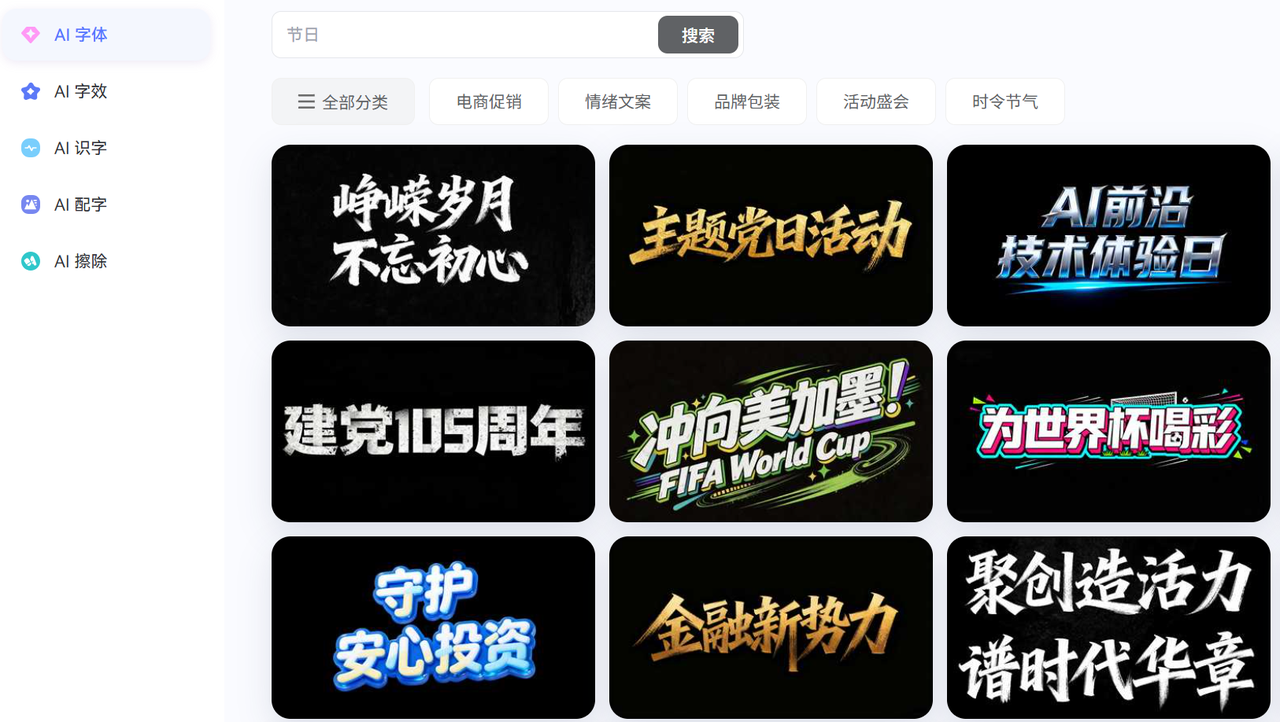
艺术字体下载合集,从基础到创意一站找齐
海报标题、品牌Logo、包装上的大字,用常规黑体宋体总显得太平淡。艺术字体自带视觉张力,一笔一画都有设计感,能让普通排版立刻变得有辨识度。但找艺术字体比找常规字体麻烦,很多平台的艺术字分类里鱼龙混杂,下载下来发现效果远不如预览图。这篇文章分享的五个渠道,从中文特效生成到海外精选库都有,帮你缩小搜索范围。
字由的分类下有不少风格强烈的字体,笔画带有装饰性细节,适合做海报主标题或者品牌标识。文艺分类则偏向优雅精致,适合做展览标题或者高端包装。这种按气质划分的方式比单纯按书体名称搜索更直觉,知道自己想要什么感觉但叫不出具体风格名时,点进对应分类浏览效率更高。
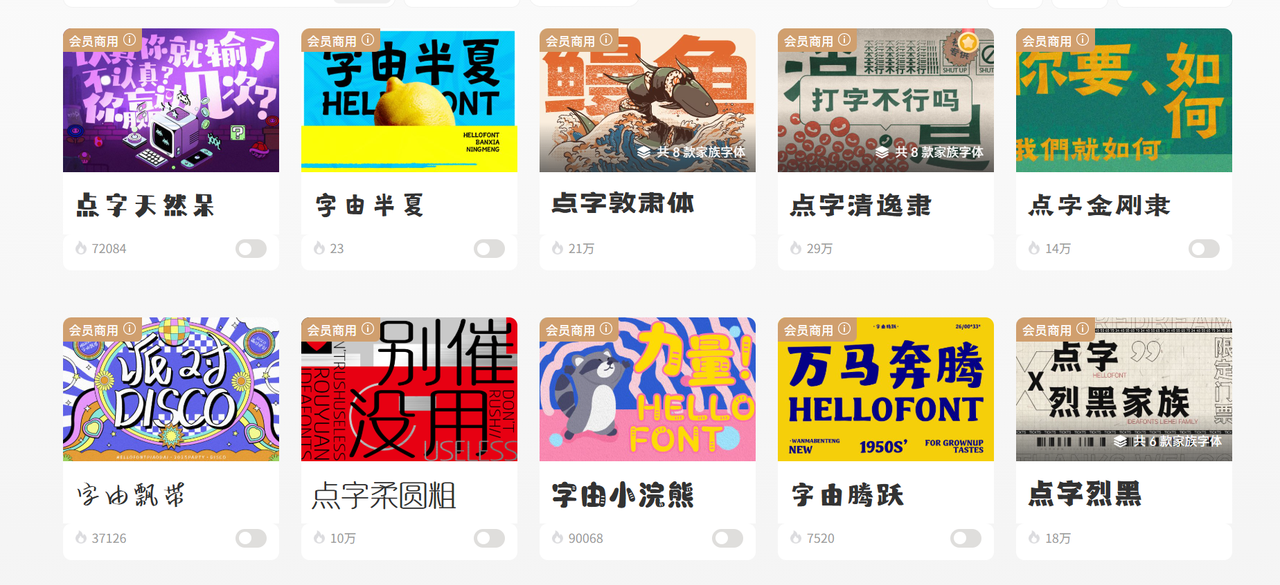
预览环节对艺术字体尤其重要。很多艺术字体在小图预览时效果不错,放大后才发现笔画细节粗糙或者字符显示不全。字由的预览框支持输入自己的文案,调整到实际使用字号后查看效果,确认清晰度再激活。激活后字体直接出现在设计软件里,不需要重启程序,试错成本很低。如果预览时发现某款艺术字体的西文部分设计得比较敷衍,和中文字形不匹配,可以立刻换另一款,避免了装完才发现不合适的尴尬。
需要把艺术字体效果再往上提一档时,字由的AI字效可以帮忙。这个工具在网页版里就能用,打开浏览器选中已激活的艺术字体,再选一个特效模板,可以给文字叠加发光、投影、渐变或者金属质感。基础面板调节字号粗细,进阶面板调整配色和效果强度,几分钟内就能拿到一张带复杂特效的PNG图片。这个功能和字体库是打通的,先在库里找到喜欢的艺术字形,再用AI字效加料,两者配合能做出常规字体文件本身实现不了的视觉效果。免费用户每日有算力额度,登录赠送的点数足够应付日常轻量使用。
2、Mockofun
Mockofun是一个在线设计工具,除了模板和图形外,也提供了字体特效生成功能。用户可以在网页里直接输入文字,选择艺术字体和特效风格,生成带设计感的标题图片。这个工具对不会用Photoshop、但又需要快速出一张带艺术字效果图片的用户比较友好。
生成的图片可以直接下载使用,也可以继续在线编辑调整。作为艺术字体下载的补充渠道,Mockofun的优势在于即开即用,不需要安装任何软件,临时在其他电脑上也能操作。对于需要快速出概念图、确认方向后再做精稿的场景,这里的生成速度比较实用。网站上还提供了不少设计模板,可以直接把生成的艺术字放进模板里出整体效果图。
3、DesignCuts
DesignCuts是一个设计资源包平台,经常推出包含多款字体的创意包。这些字体包通常围绕特定主题或者风格 curated,比如复古风格包、手写风格包、现代无衬线包等,包内的字体在视觉上比较协调,适合需要成套使用的情况。
对于需要艺术字体下载、且希望一次获取多款协调字体的用户来说,这种打包方式比逐个下载更高效。包内的字体授权信息在详情页清楚标注,大部分是允许商用的。DesignCuts还会不定期推出免费资源包,关注这些活动可以以零成本获取高品质字体包。对于做系列物料、需要保持字体风格一致性的项目来说,这里的主题包比较实用。
4、YouWorkForThem
YouWorkForThem是一个高品质设计资源站,字体板块里有不少独立设计师和字体厂牌的作品。和大型免费字体站不同,这里的选品偏向精品路线,很多字体在字形设计和完成度上比较高。艺术字体方面,平台上收录了不少Display展示字体和创意字体家族,风格从实验性到商业性都有覆盖。
每款字体都有详细的展示图,多字重家族会展示不同字重的对比效果。对于需要艺术字体下载、且对字体品质有一定要求的用户来说,这里的选品经过一定筛选,踩雷概率比较低。平台上除了字体外还有图形、模板等其他设计资源,做项目时可以在同一个平台补充素材,省去了在多个网站之间切换的麻烦。
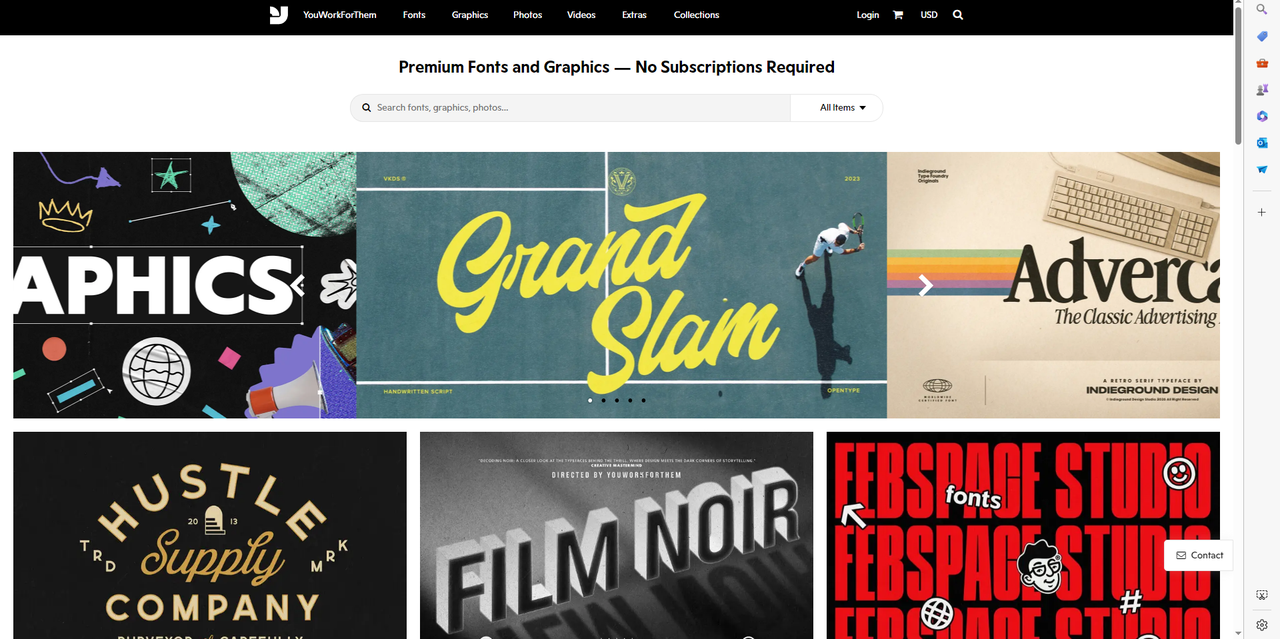
5、1001 Fonts
1001 Fonts的Artistic Fonts标签下目前收录了九百多款艺术字体,数量比较可观。顶部的标签云包括artistic、decorative、handwriting、calligraphy、modern、brand identity等关键词,点击就能快速筛选对应风格。想做复古海报就点decorative或者vintage相关标签,做现代品牌就点modern或者brand identity,找字路径比较清晰。
平台上提供Commercial free筛选按钮,勾选后只显示允许免费商用的字体,做商业项目时比较省心。每款字体都支持在线预览,输入框里填自己的文案,实时看到效果后再决定是否下载。下载按钮直接获取字体文件,安装到系统后在设计软件里就能调用。作为艺术字体下载的渠道,1001 Fonts的资源量和筛选维度都比较够用,适合批量探索不同风格的艺术字体。
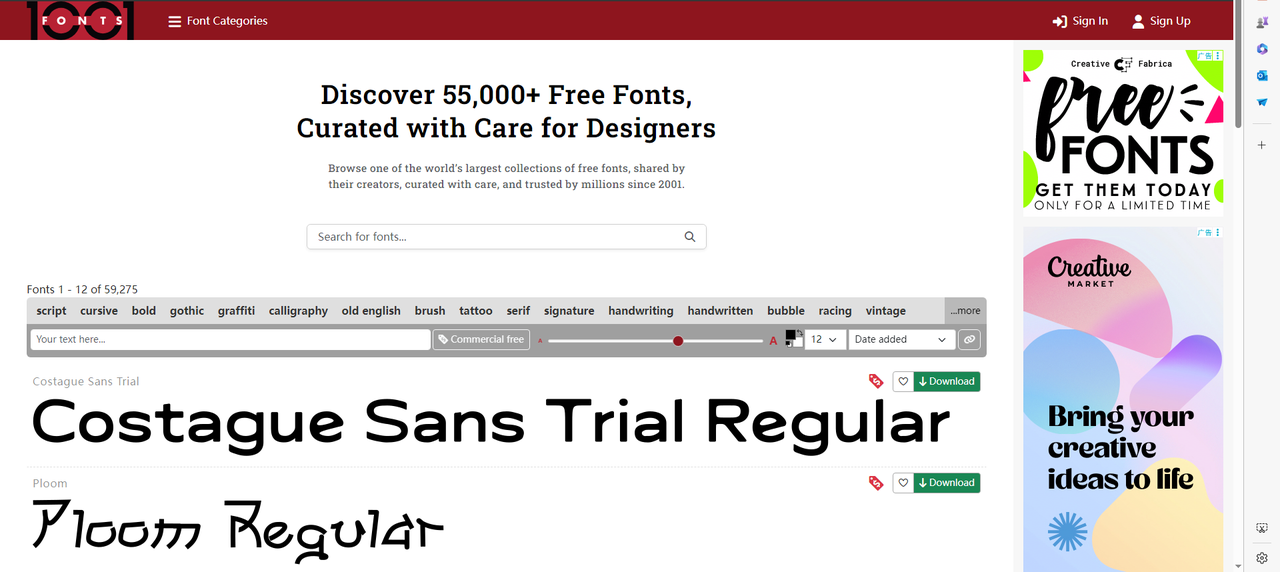
做海报标题或者品牌标识,字由的艺术字体分类配合AI字效,从找字形到加特效比较顺畅,作为艺术字体下载的主力渠道效率不错。1001 Fonts资源量大、筛选维度多,适合批量探索。YouWorkForThem在品质方面比较突出,选品经过筛选。DesignCuts的字体包适合成套使用,风格协调性好。Mockofun则胜在即开即用,不需要安装软件。